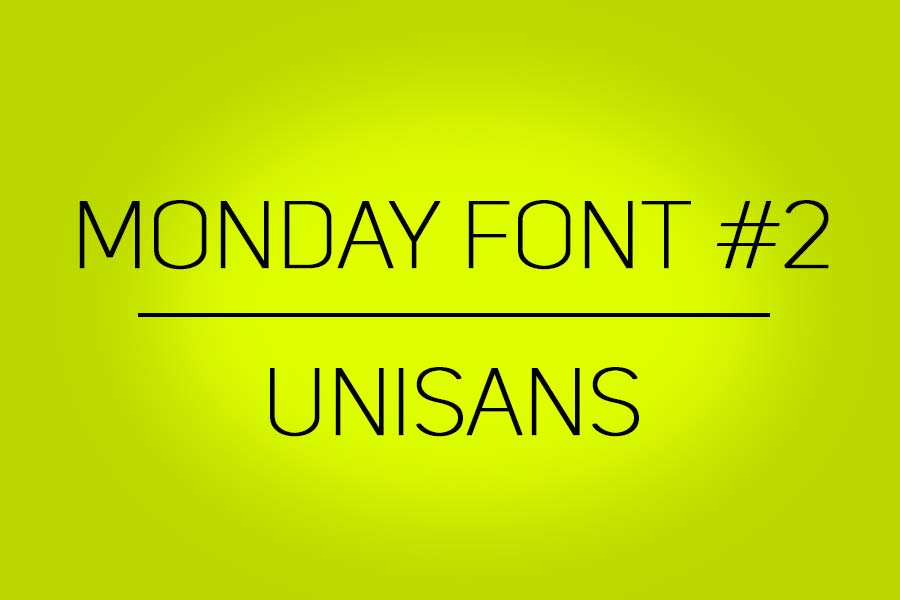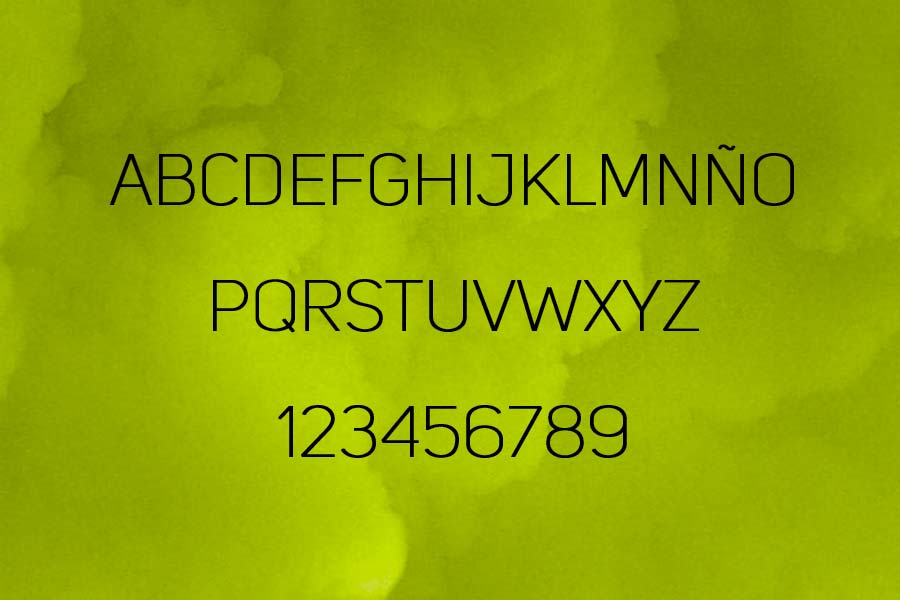
Volvemos con la #2 edición de nuestra selección personal de fuentes tipográficas. Seguimos con otra tipo sans serif, fina y con mucho estilo.
Uni Sans / Sans Serif
Diseñada por Svet Simov, Ani Petrova y Vasil Stanev.